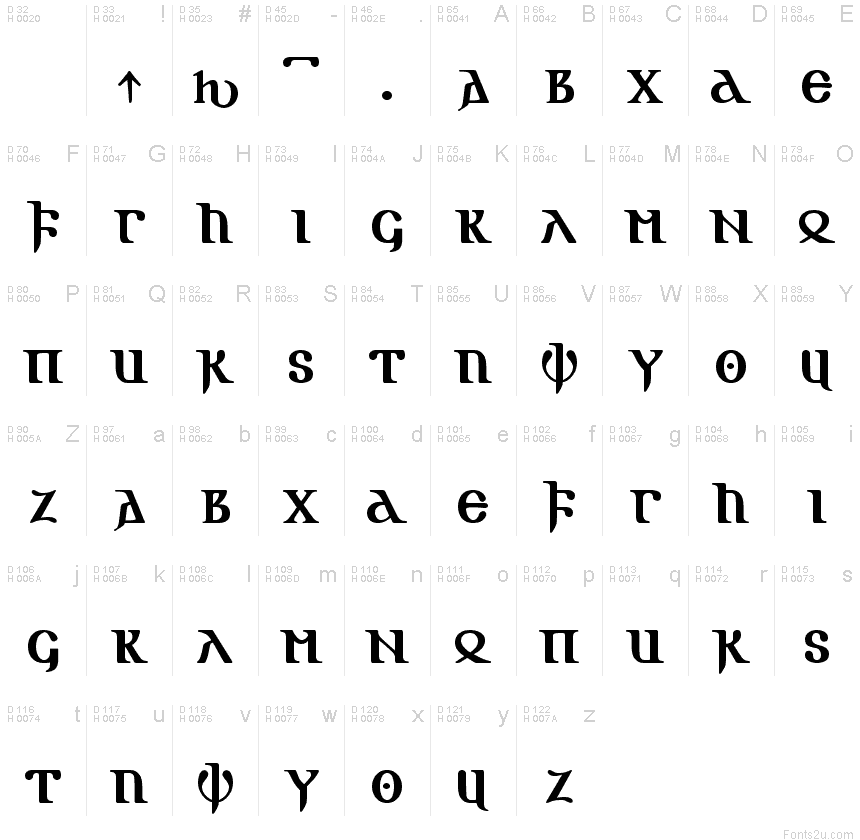
Gotik AOE od Astigmatic One Eye Typographic Institute to darmowy gotycki krój pisma o wyrazistym, niemal rzeźbiarskim charakterze. Grube, mocne linie układają się w ciasne pętle i nieoczekiwane kąty, nadając każdemu słowu nastrojową, średniowieczną wagę, bez zbędnego przeładowania czy problemów z czytelnością. Litery sprawiają wrażenie wykutych w kamieniu, a zaokrąglone wewnętrzne krzywizny dodają im płynności i życia.
Ten darmowy font świetnie sprawdza się na okładkach książek fantasy, w tytułach gier, logotypach zespołów metalowych lub alternatywnych, plakatach mrocznych wydarzeń, wzorach tatuaży oraz w nastrojowym brandingu. Użyj Gotik AOE w większym rozmiarze, aby pozwolić wybrzmieć dramatycznym krzywiznom i ostrym cięciom. W tekście głównym połącz go z czystym, geometrycznym bezszeryfowym krojem, aby zachować przejrzystość i równowagę układu.